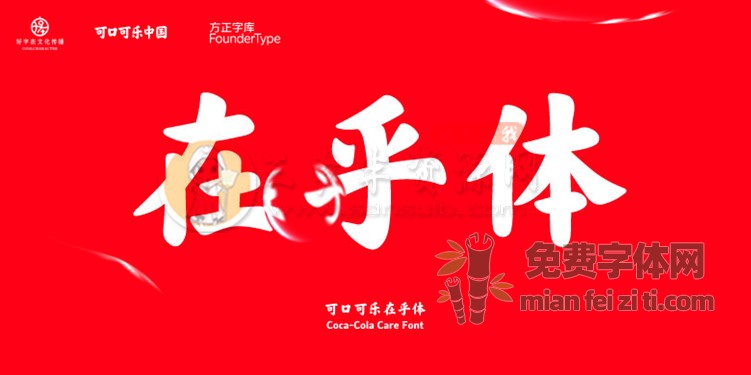
字体风格: 楷书
全球知名品牌可口可乐公司在中国市场深耕了41年,在这里经营、生活、成长,也深受中华文化和精神启发。可口可乐企业价值观和中国文化中的“在乎”很有共鸣。“在乎”二字,细细品来,“在”,如破土幼芽,标示生命、初始、本能;“乎”,是将气息稳定、呼吸平稳。“在乎”,有“放在心上”之意。这份温和、不张扬的关怀和担当,是中国文化的独特表达,也是可口可乐中国的企业价值观。
为了致敬这份文化共鸣,可口可乐中国以重返中国早期的老商标字体为灵感原点,邀请汉字文化推广机构好字在和方正字库一起,创造了一套字体,命名为“可口可乐在乎体”。
作为一款全新的品牌定制字体,“在乎体”从情怀出发,用具象的设计方法,借由每一笔一划,表达中国人对“在乎”的理解和诠释——圆融、力量、担当、从容、进取,希望在数字化时代,为大家提供一种有人情味的字体选择。用在乎体,写在乎的事,给在乎的人。
可口可乐在乎体含义:
全球知名品牌可口可乐公司在中国市场深耕 41 年,可口可乐在这里经营生活成长也深受中华文化和精神的启发。
可口可乐企业价值观与中国文化中的在乎很有共鸣,同时这份温和不张扬的关怀担当也是中国文化的独特表达等。
而这也是可口可乐中国的企业价值观,为致敬这份文化共鸣可口可乐中国以重返中国市场早期老商标字体为灵感。
为此邀请汉字文化推广机构好字与字体设计师方正字库联合推出可口可乐在乎体,作为可口可乐品牌的定制字体。